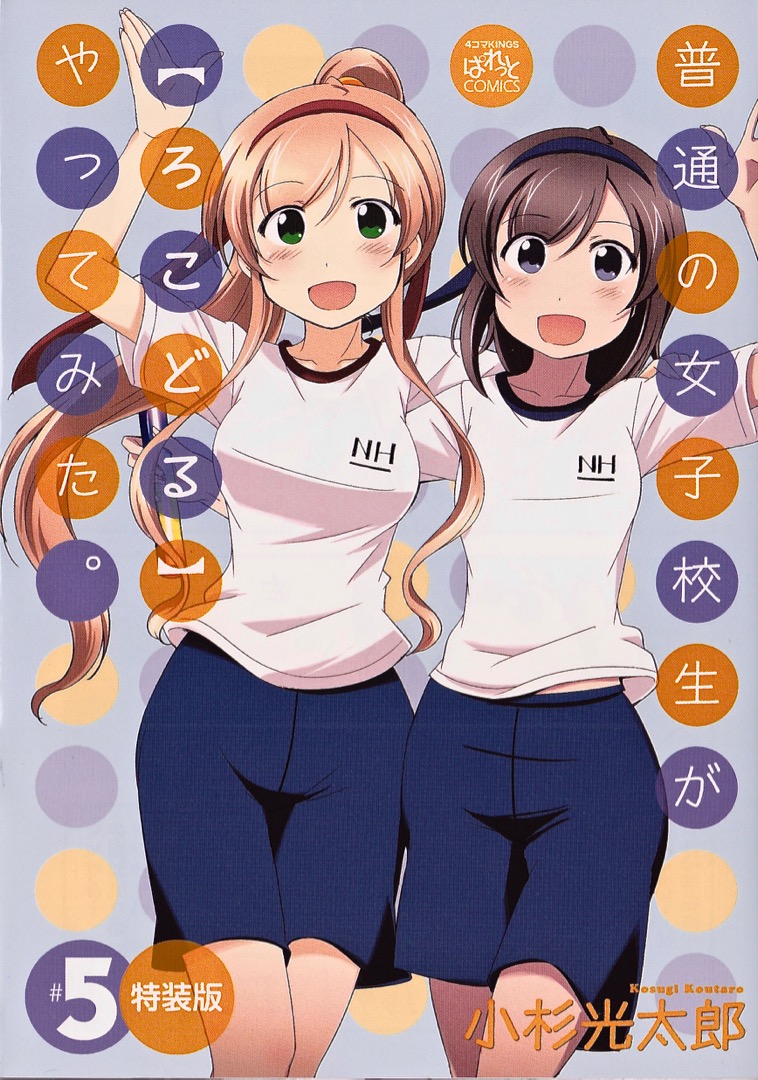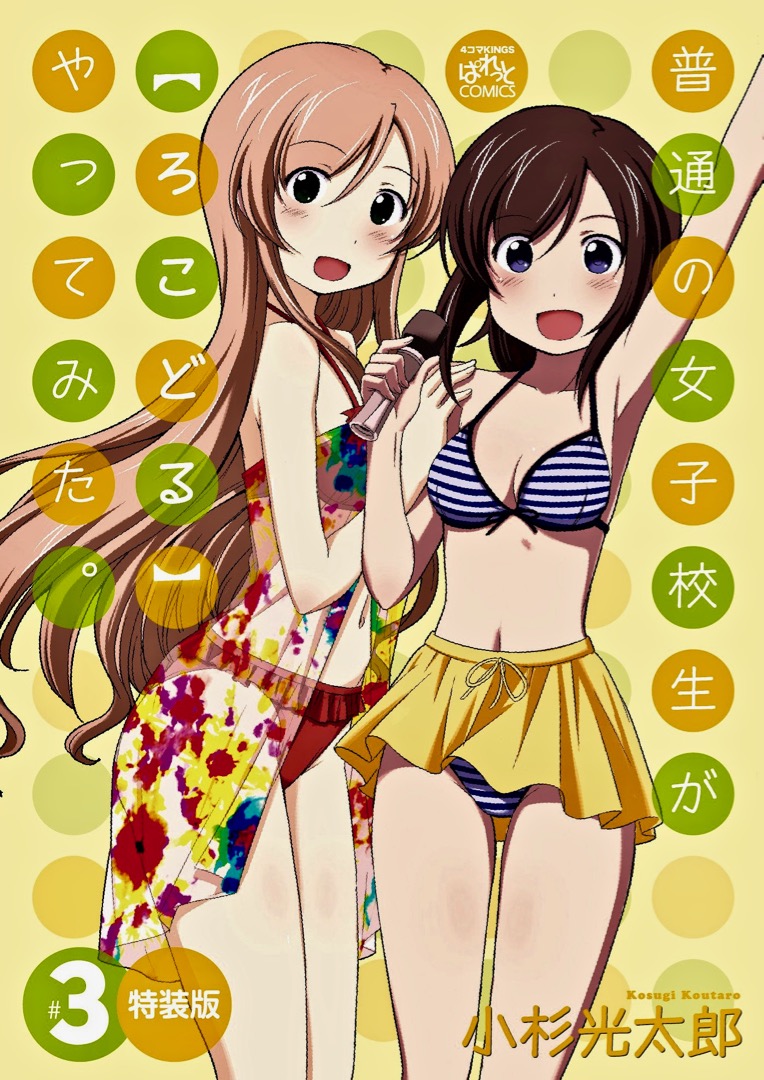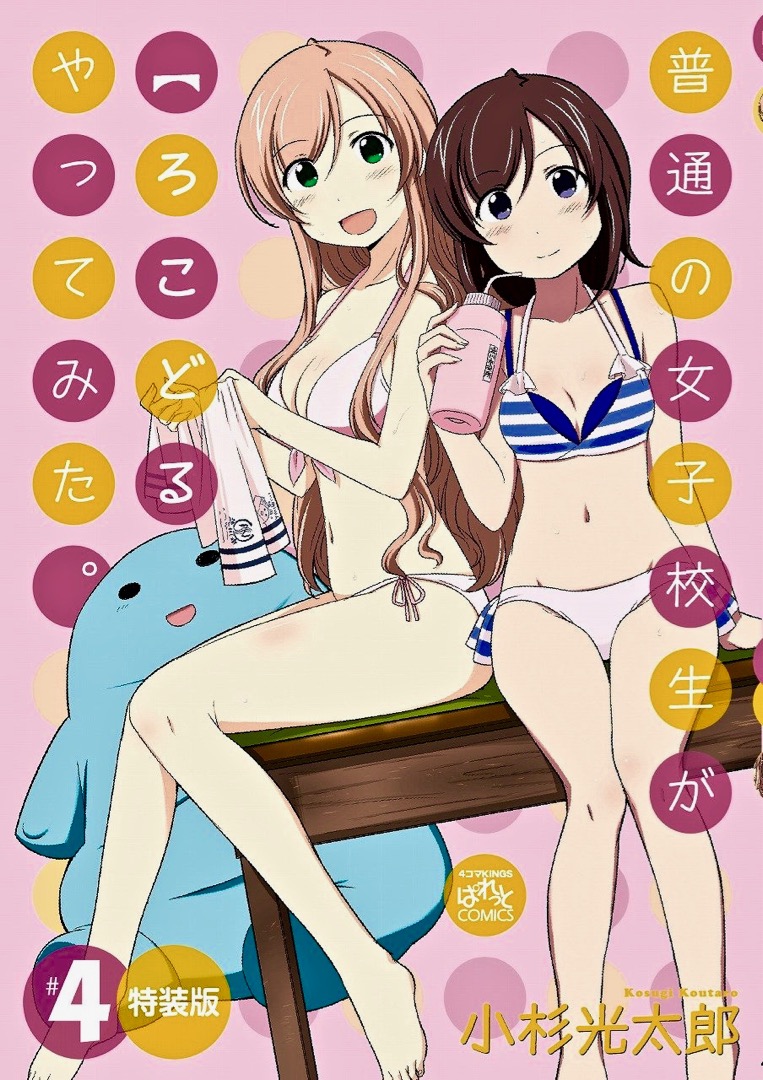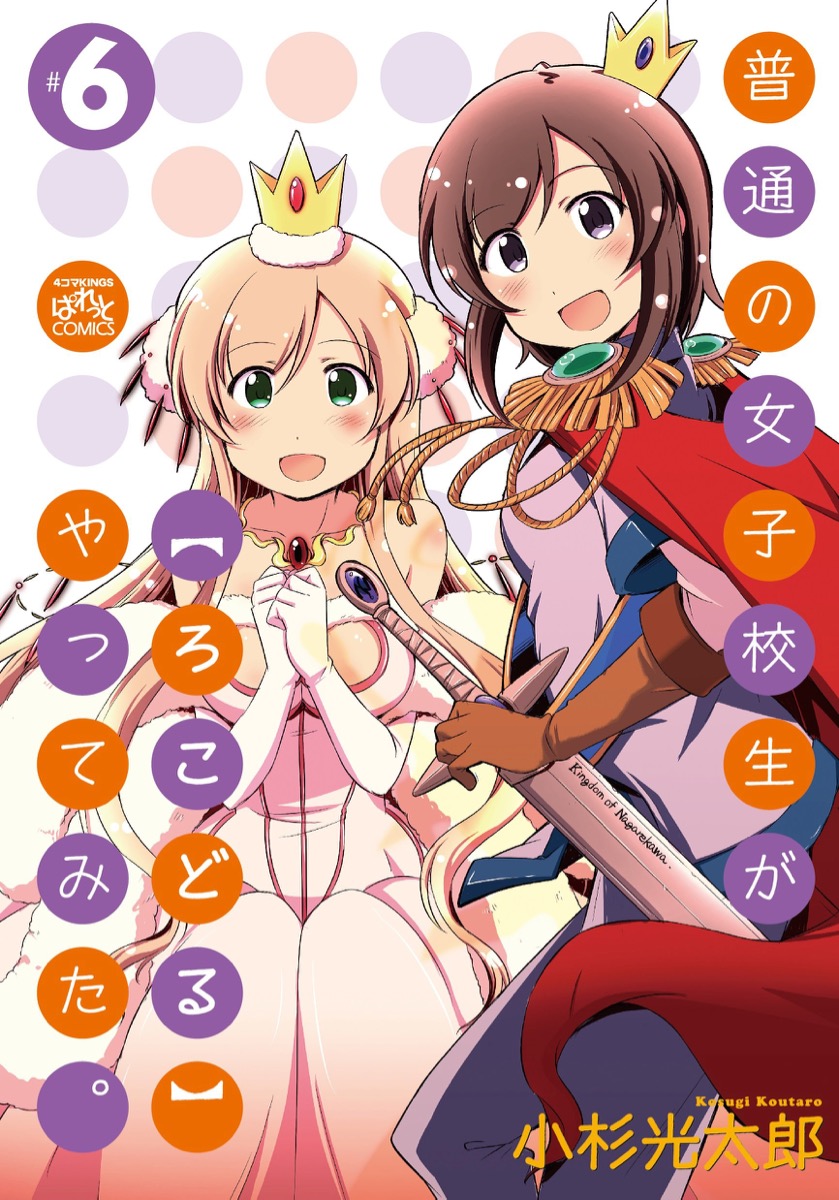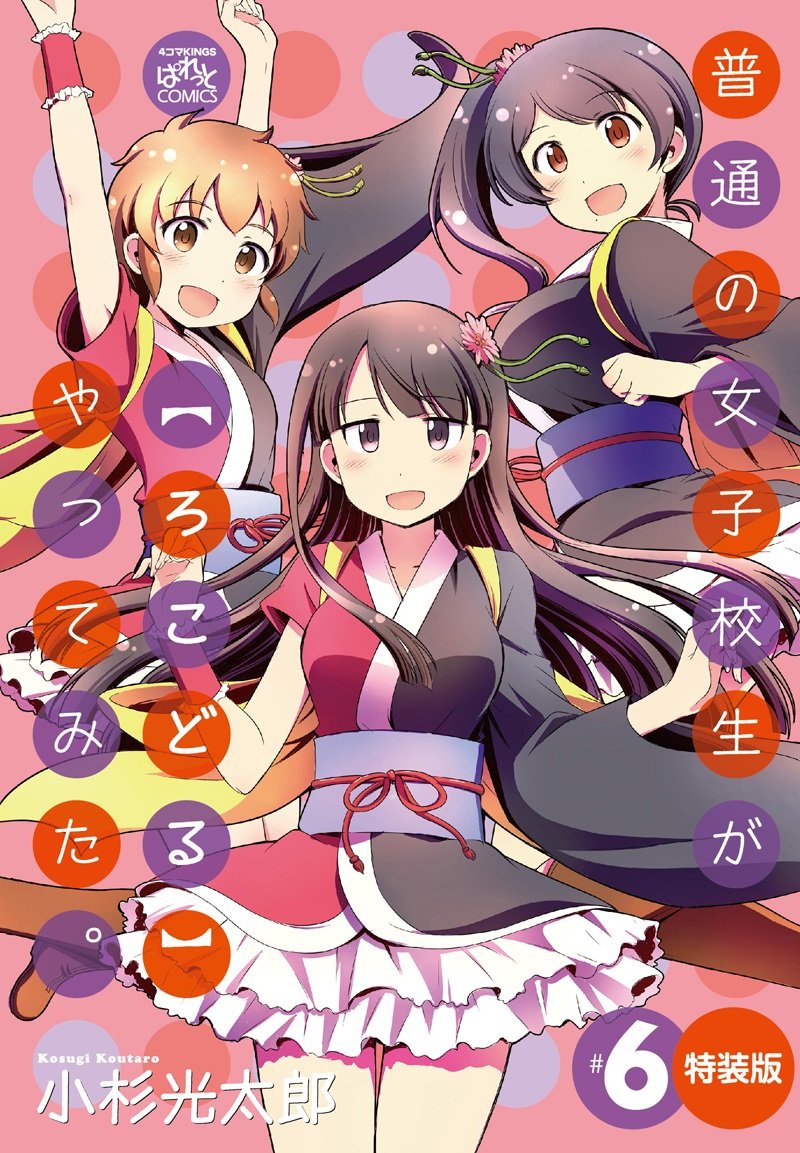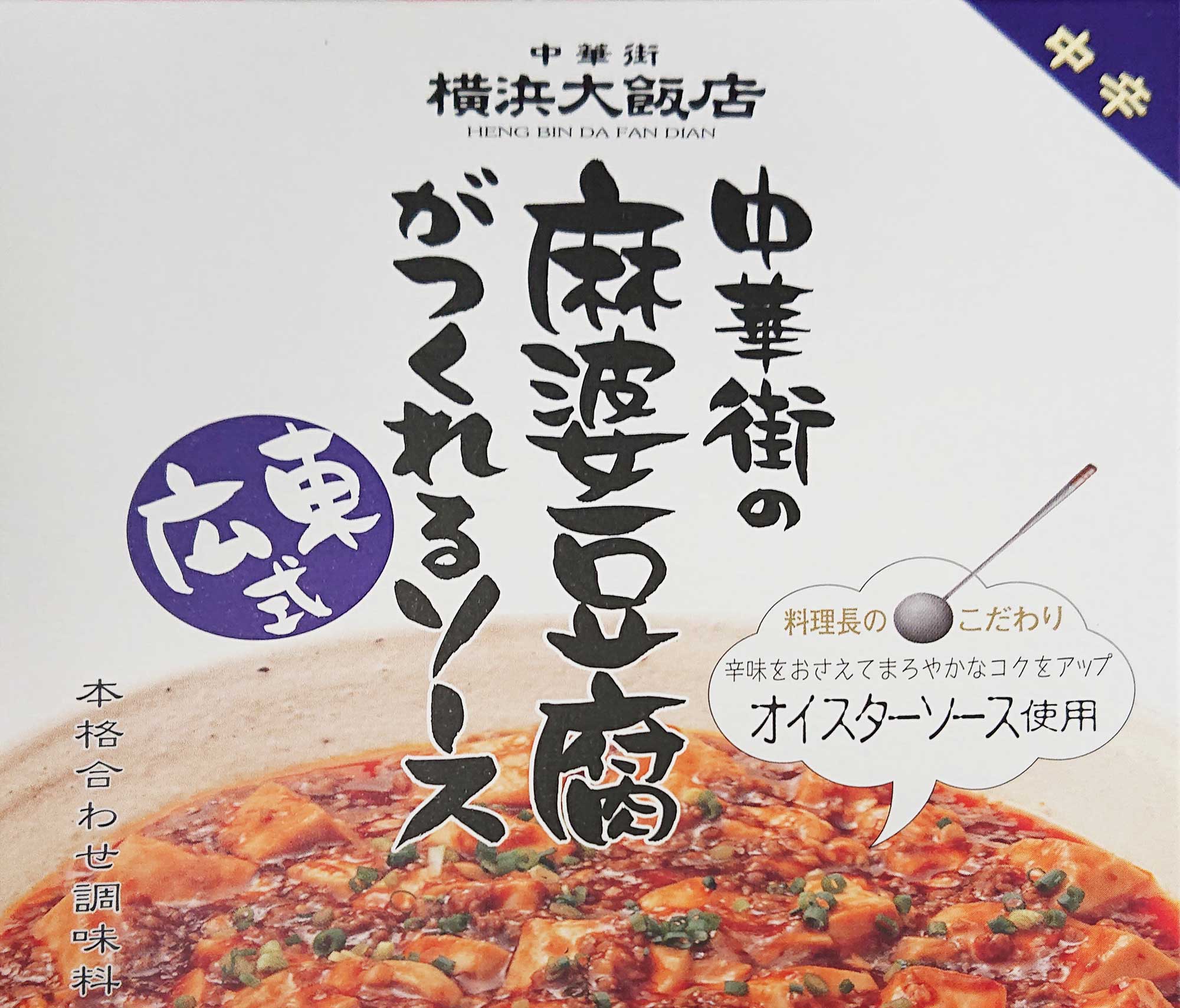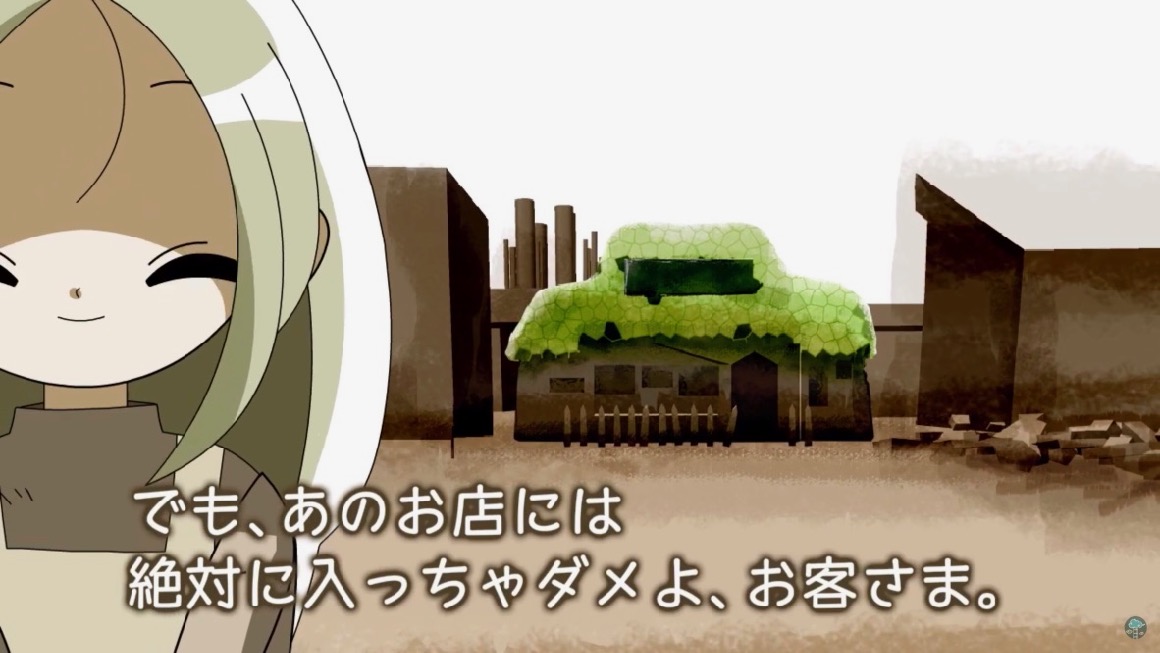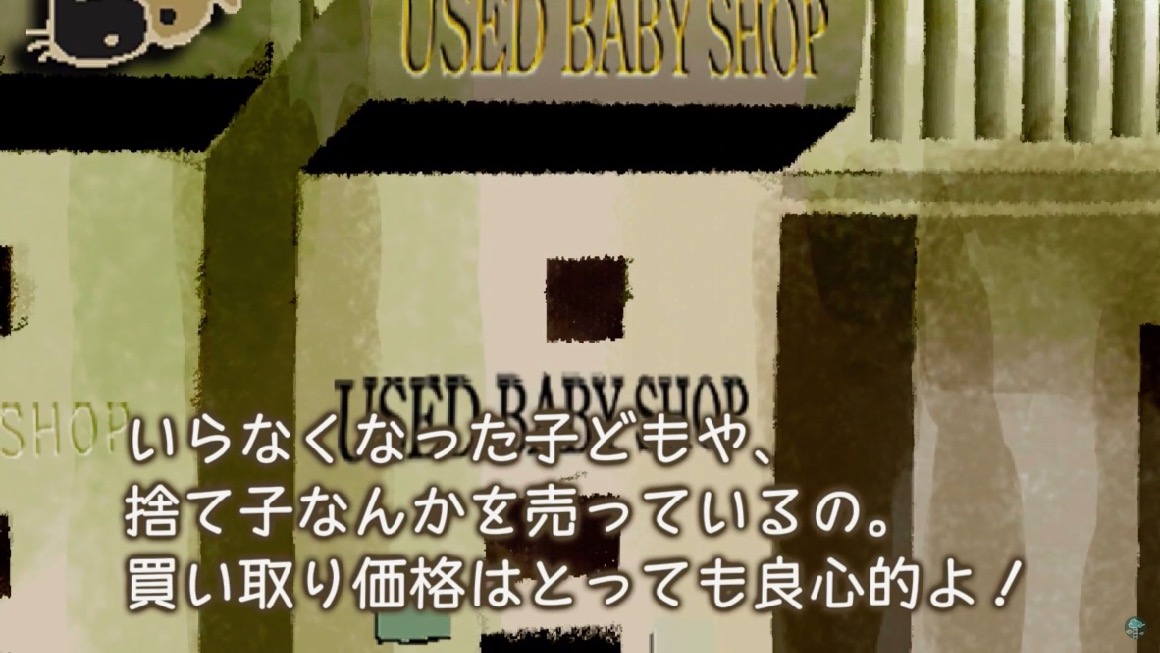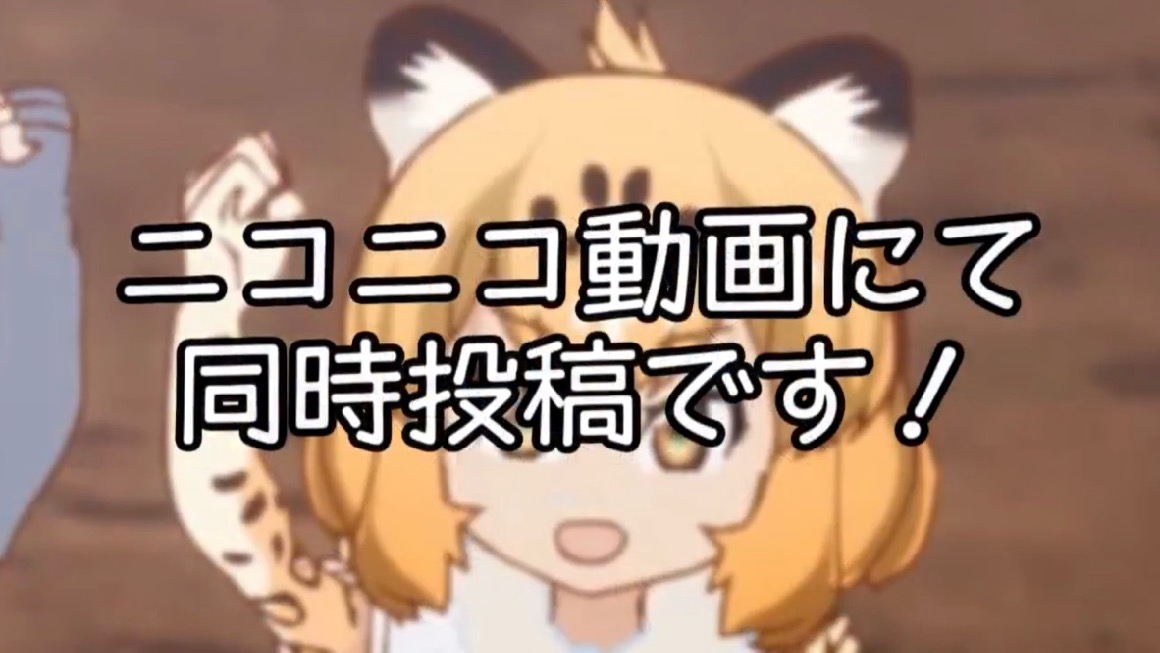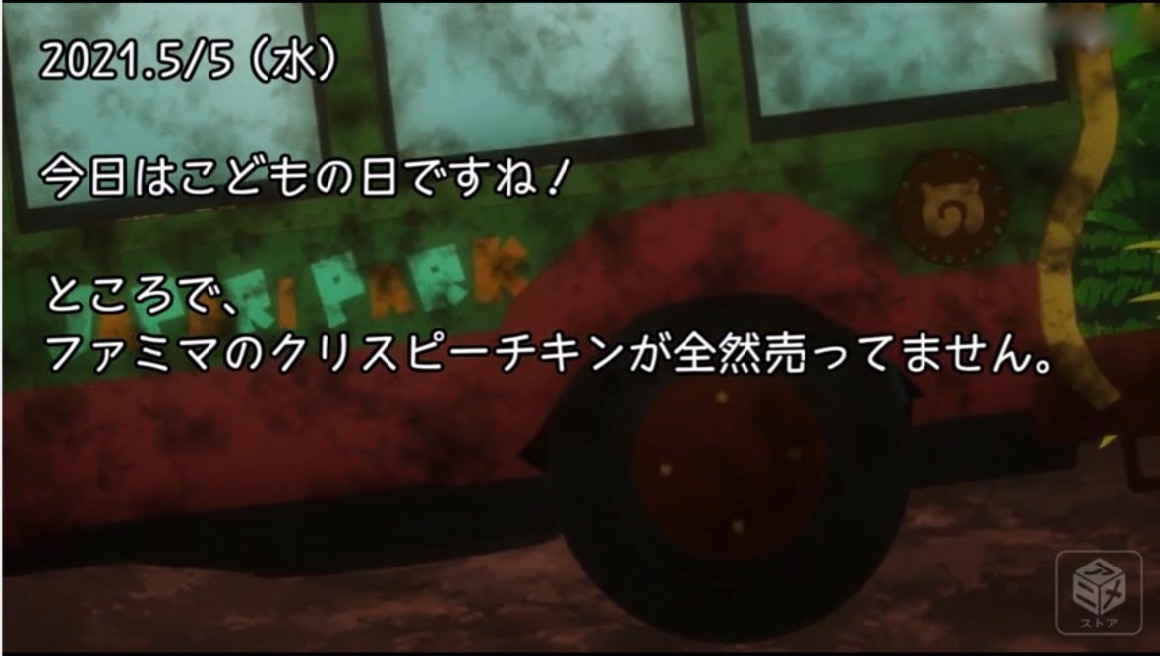
ファイラのUIフォントなどにも使っています。
絵本  さとうゆたか  2010年6月25日(金) 10:01
表紙から本文まで、すべてセプテンバー書体が使われています。
書  名:月をぬすんだ子供
著  者:野上彰
絵   :斉藤繁次
デザイン:川上一
発  行:徳島県立文学書道館
発行者 :瀬戸内寂聴
懐かしい本を思い出しました。
古いバージョンの貴重なセプテンバーフォントです…。
スライドデータ  さとうゆたか  2023年4月17日(月) 16:22
Laravel3に入門してみる #laraveljpcon
LOOK「ふんだんパイン」  takumi  2023年2月2日(木) 14:13  HP
LOOKのパッケージでセプテンバーが使われていました。
「ふんだんパイン」の文字ですが、機械的に太らせてあるようです。
さとうゆたか  2023年2月2日(木) 14:19 [修正]
この書体、使用例が少ないんですよね〜。
プライベートな物に使っているのかもしれないですね。
着付け教室のチラシ  さとうゆたか  2023年1月25日(水) 16:02
今朝の新聞に折り込まれていた。
YouTubeのサムネイル  ちょこちょっこ  2022年12月28日(水) 15:39
最高の文字は、ルイカ系ですね。
制作者は、AdobeFontsを利用してるのかな。
デコ文字  さとうゆたか  2022年9月18日(日) 9:31
好きな文字を1文字ずつ打てます。
LINEの絵文字(デコ文字)。
アニメ「SPY×FAMILY」  takumi  2022年5月23日(月) 12:26  HP
放送中のアニメ「SPY×FAMILY」の第7話劇中で「セプテンバー」を見つけました。
細いものを太らせて使っているっぽいですが…。
AdobeFontsのN3を使ったんだけど、太さが足りなくて太らせたんでしょうね…。
N4とかN5の太さのフォント商品もあるんですけど…。
セプテンバー発見  ゆう  2022年3月26日(土) 20:13
借金絡みの広告?
追記  ゆう  2022年3月26日(土) 20:16  Mail [修正]
ウェイトはN3なので、AdobeFonts経由と思われます
まだ使用例が少ない書体ですので、貴重ですね。
ニコニコ動画  さとうゆたか  2022年3月5日(土) 16:52
TKJ(じゃーろんず)